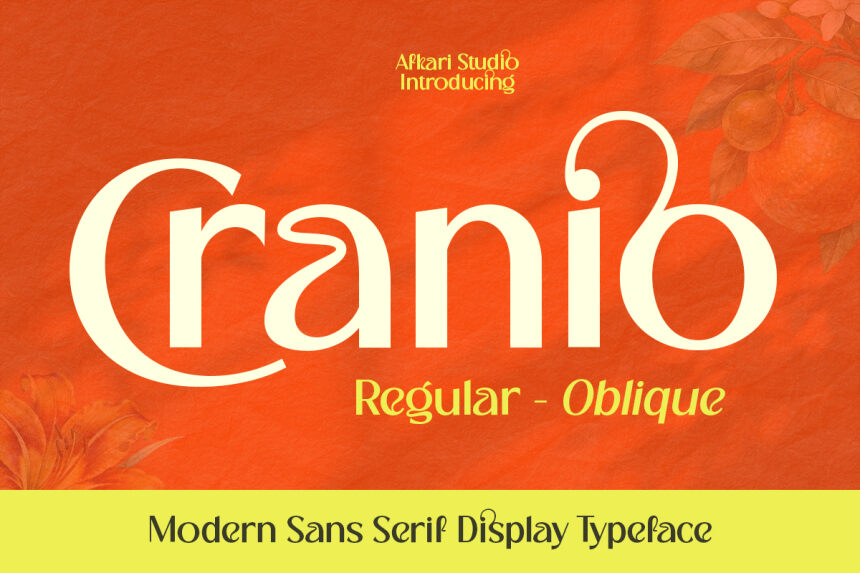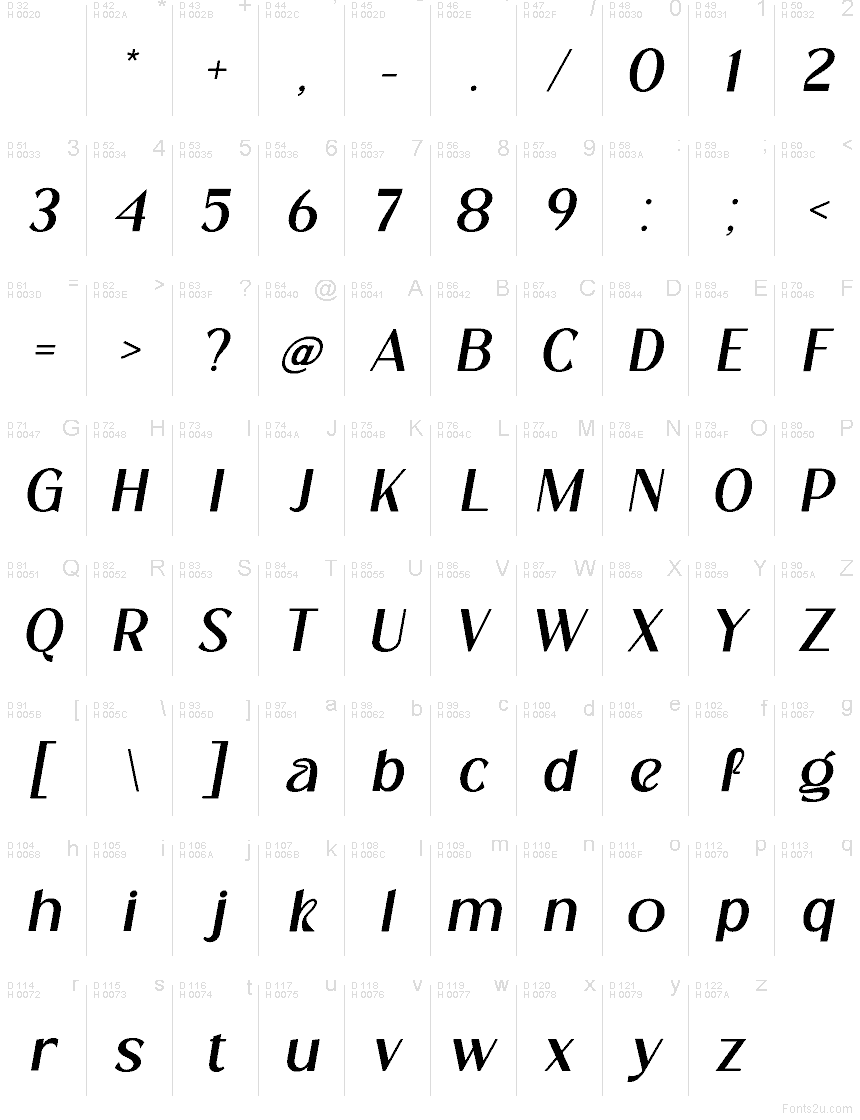
Cranio Oblique di Afkari Studio è un carattere serif display retrò gratuito, caratterizzato da un'inclinazione editoriale fluida e da un inconfondibile stile anni '70. Le lettere fondono contrasti netti con giunture morbide e sinuose: il font appare elegante a un primo sguardo, ma diventa giocoso man mano che le forme arrotondate e i dettagli a uncino iniziano a ripetersi.
Si adatta perfettamente a testate di riviste, packaging di boutique, copertine di album, branding di ristoranti e titoli di poster in cui quel mood retrò sofisticato può davvero fare la differenza. Essendo un font gratuito, è ideale anche per lookbook, titoli di copertina e brevi firme di brand. Usalo quando vuoi che un titolo risulti elegante e leggermente teatrale, senza però risultare eccessivo.